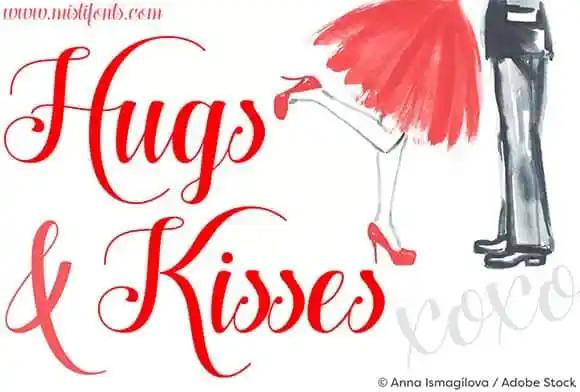
Hugs and Kisses Xoxo Font – Download Grátis
A fonte Hugs and Kisses xoxo é uma elegante tipografia script ideal para diversas aplicações, desde cabeçalhos até cartões de agradecimento e embalagens personalizadas. Desenvolvida por Misti’s Fonts, ela oferece uma variedade imensa de possibilidades criativas. Seja para usar em selos, sobrepostas ou como fonte de chamamento nas suas próximas campanhas de marketing, a Hugs and Kisses xoxo é certamente um atalho inteligente ao design. Não importa se você está criando materiais para festivais, arte digital, designs gráficos ou até mesmo t-shirts personalizadas – essa fonte pode fazer maravilhas em tudo que você criar. A Hugs and Kisses xoxo é a escolha perfeita para quem procura uma fonte de design que não apenas faz seu trabalho bem feito, mas também adiciona um toque especial ao seu projeto. Seja qual for o desafio gráfico que você enfrentar, a Hugs and Kisses xoxo tem tudo para torná-lo mais envolvente e memorável.